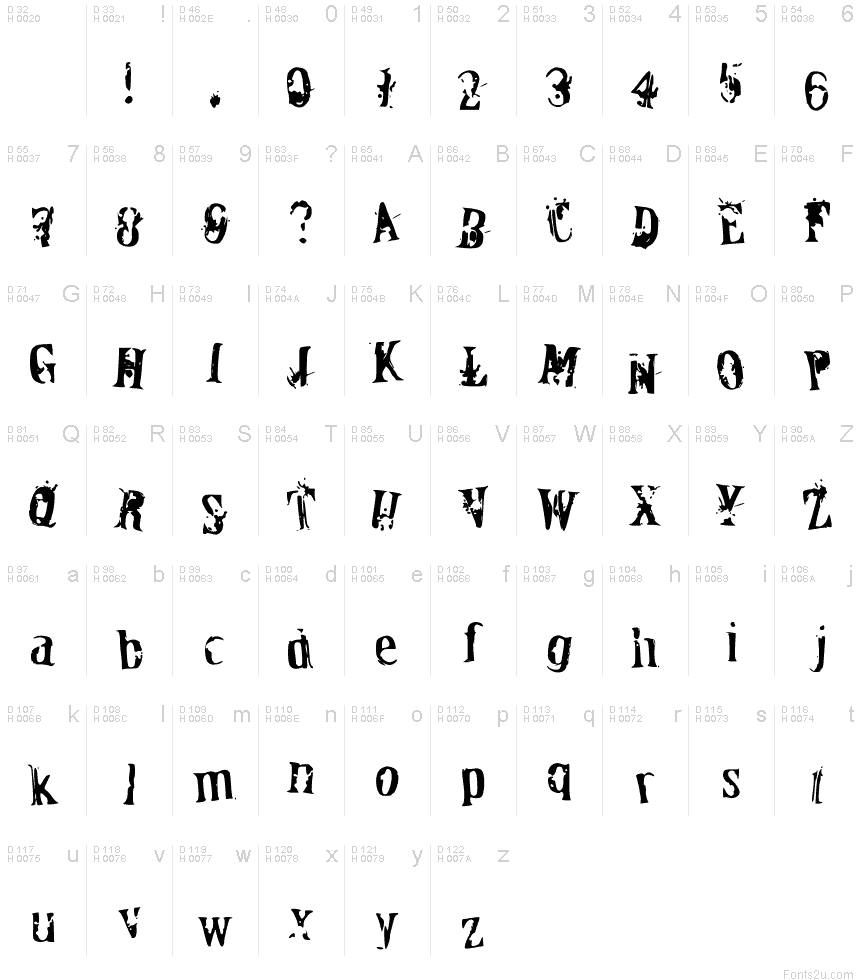
Office Down, którego twórcą jest Davy Meykens, to darmowy, zniekształcony krój typu display o charakterze plakatu horroru. Wysokie szeryfowe litery wyglądają na poszarpane, poplamione i ochlapane.
Plakaty filmów grozy to jego najbardziej naturalne środowisko, a zniszczone sylwetki mogą przywoływać na myśl stare szyldy nawiedzonych domów na ulotkach wydarzeń i grafikach mrocznych gier. Oprawy albumów muzyki metalowej lub industrialnej mogą wykorzystywać te same plamy i ścieki jako część dzieła, ale tytuły horrorów pozostają jego najbardziej przekonującym zastosowaniem ogólnym.